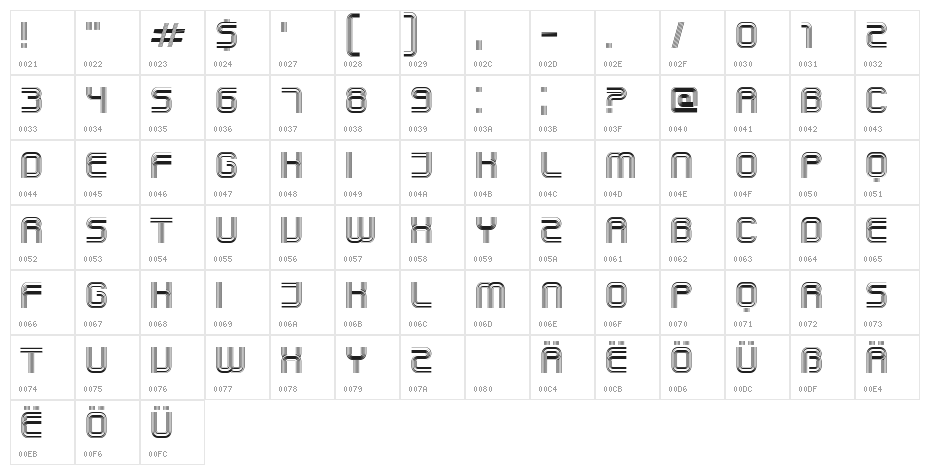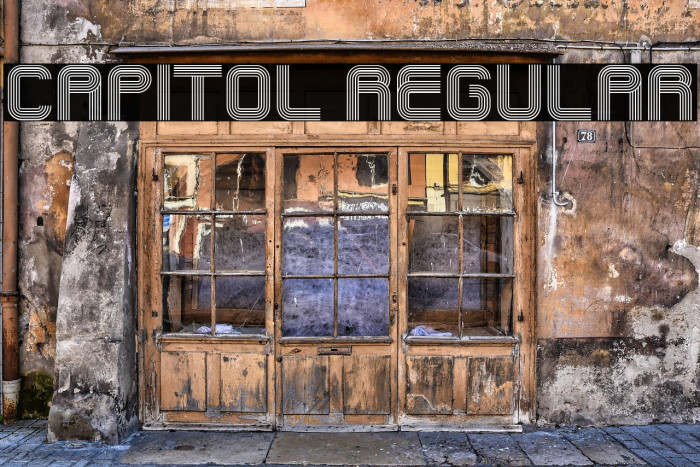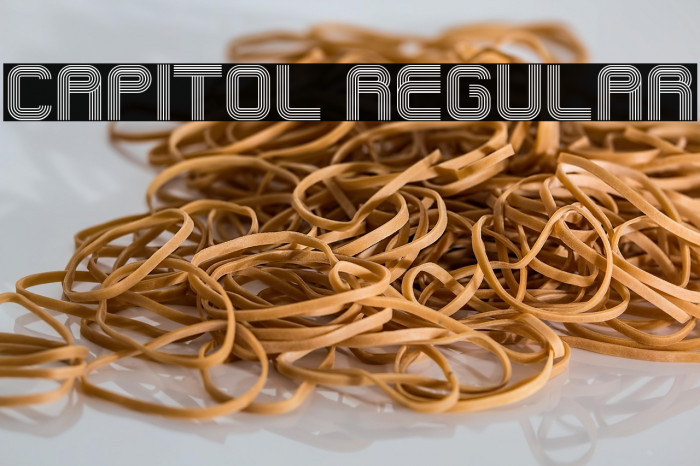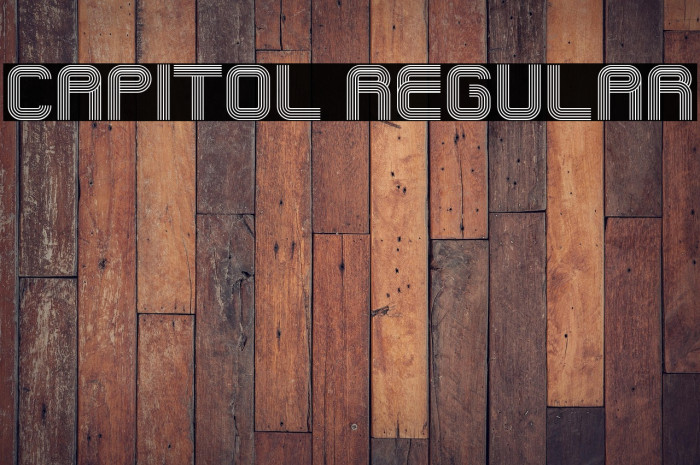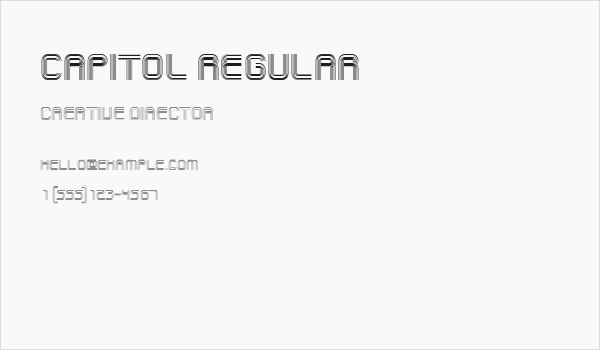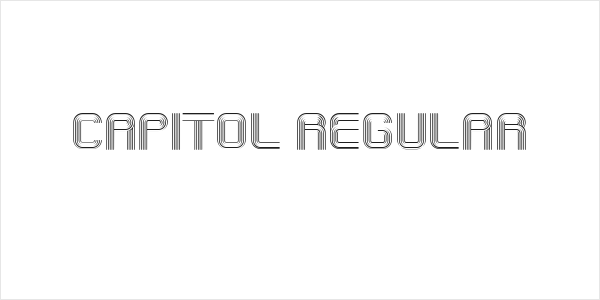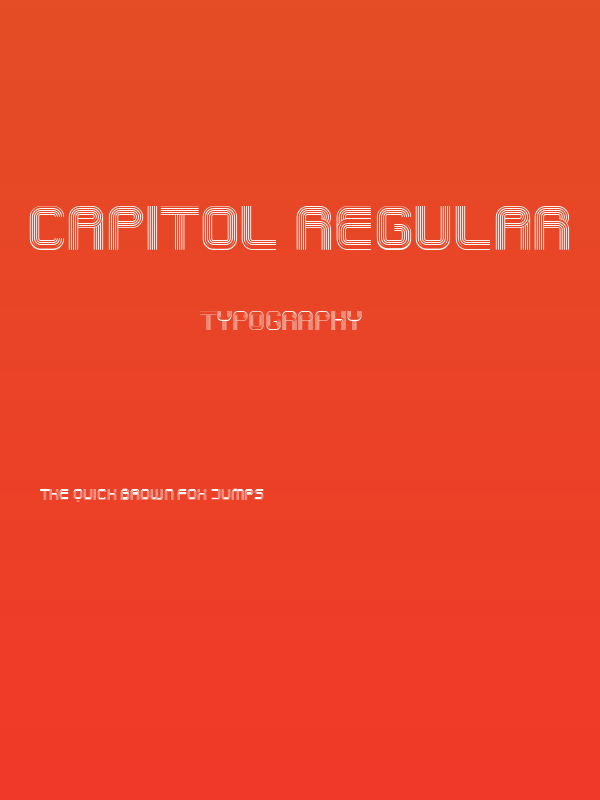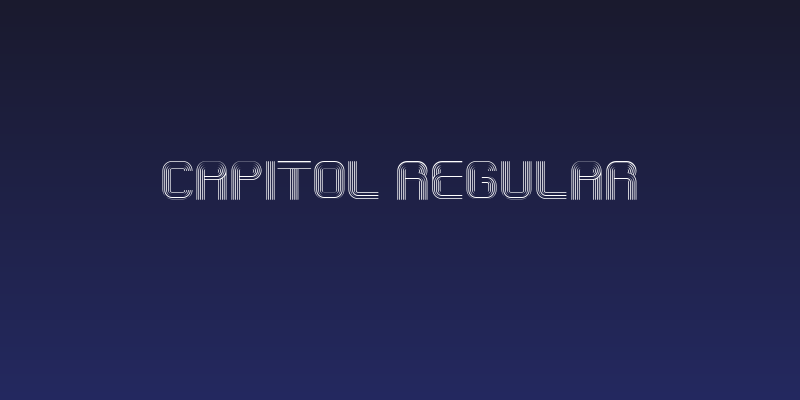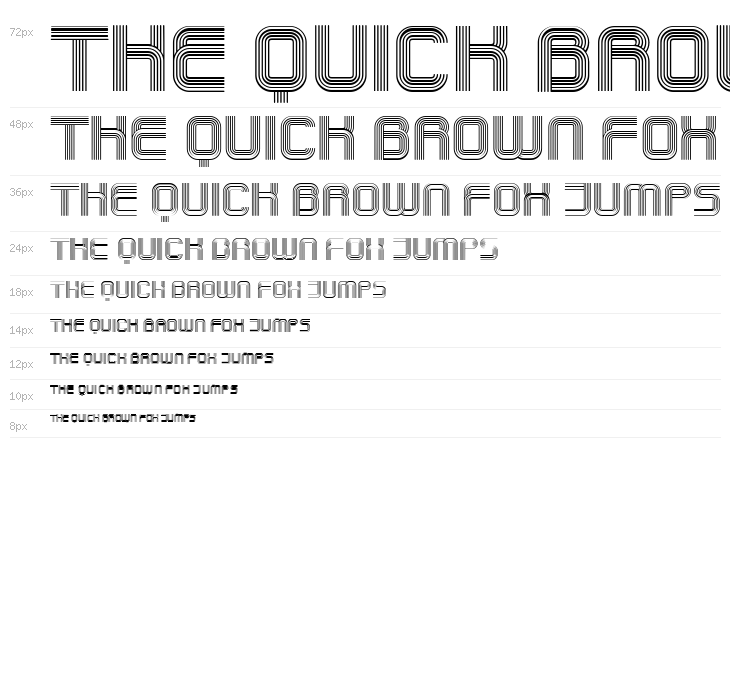
Capitol Regular Font
| Progetti proposti | Ideal for technology branding, sci-fi themed posters, modern art installations, and innovative product packaging. |